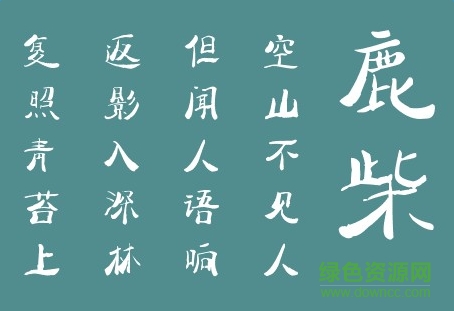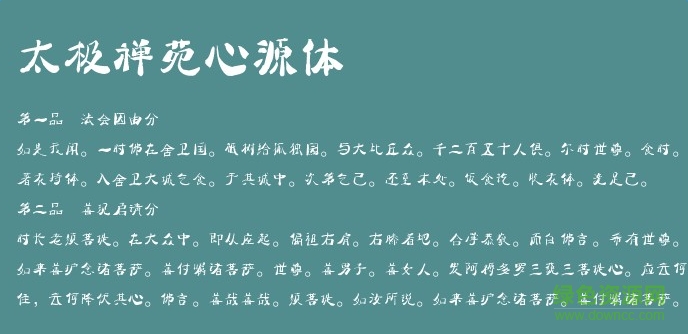
太極禪苑心源體字體是一款充滿禪意的字體,該字體包含了共6763個(gè)中文漢字,字體俊逸雋秀,可用作制作影視宣傳、海報(bào)、平面設(shè)計(jì)等,需要的朋友歡迎在綠色資源網(wǎng)下載!
太極禪苑心源體是由阿里巴巴太極禪苑員工童曉君(花名:紫摩)書(shū)寫(xiě)的一款字體原型,曉君自幼喜愛(ài)國(guó)學(xué)和佛學(xué),2015年曾在泰國(guó)短暫出家,自三年前練習(xí)書(shū)法至今,書(shū)法的練習(xí)方式以抄寫(xiě)經(jīng)書(shū)為主,她抄寫(xiě)的經(jīng)書(shū)曾被多位企業(yè)家收藏,其書(shū)法風(fēng)格雋秀清麗,欣賞其書(shū)法作品時(shí)似乎能感受到心底的平靜,在靜謐中尋找一種通向人生心靈深處的那盞明燈,字里行間透露出一種禪文化的陰陽(yáng)平和